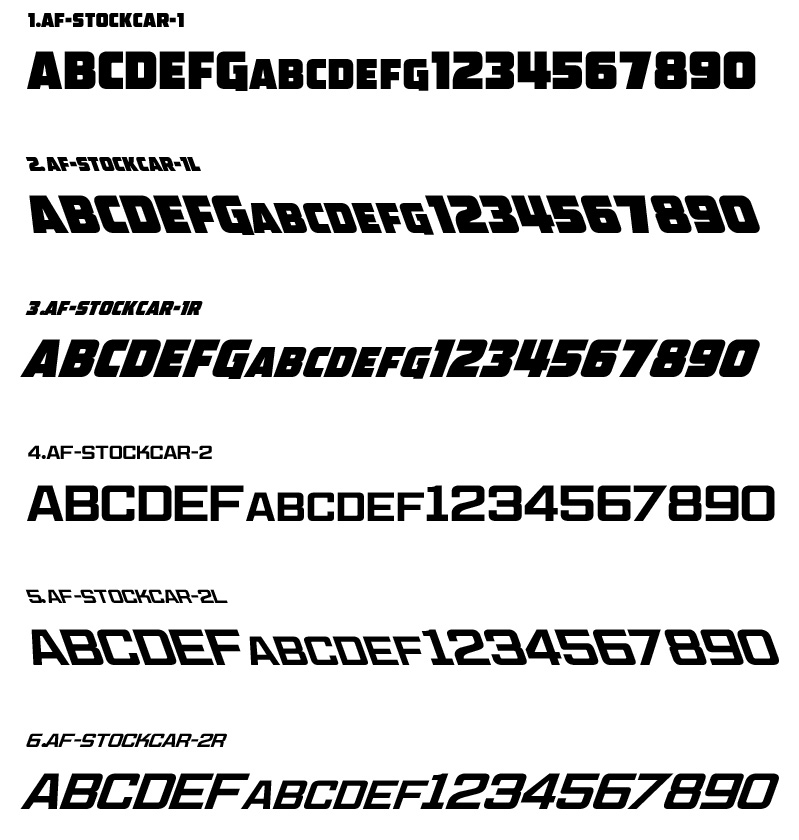
ストックカーみたいな3書体 No.1
ストックカーみたいな3書体 No.2
【収録書体】
本商品は下記6書体のセットです。
アメリカのストックカーレーシングで使われるレースカー側面に貼られる数字や文字を模した1Byte欧文デザインフォントです。
AP機能の関わらず左右斜体が利用できる便利なセットです。